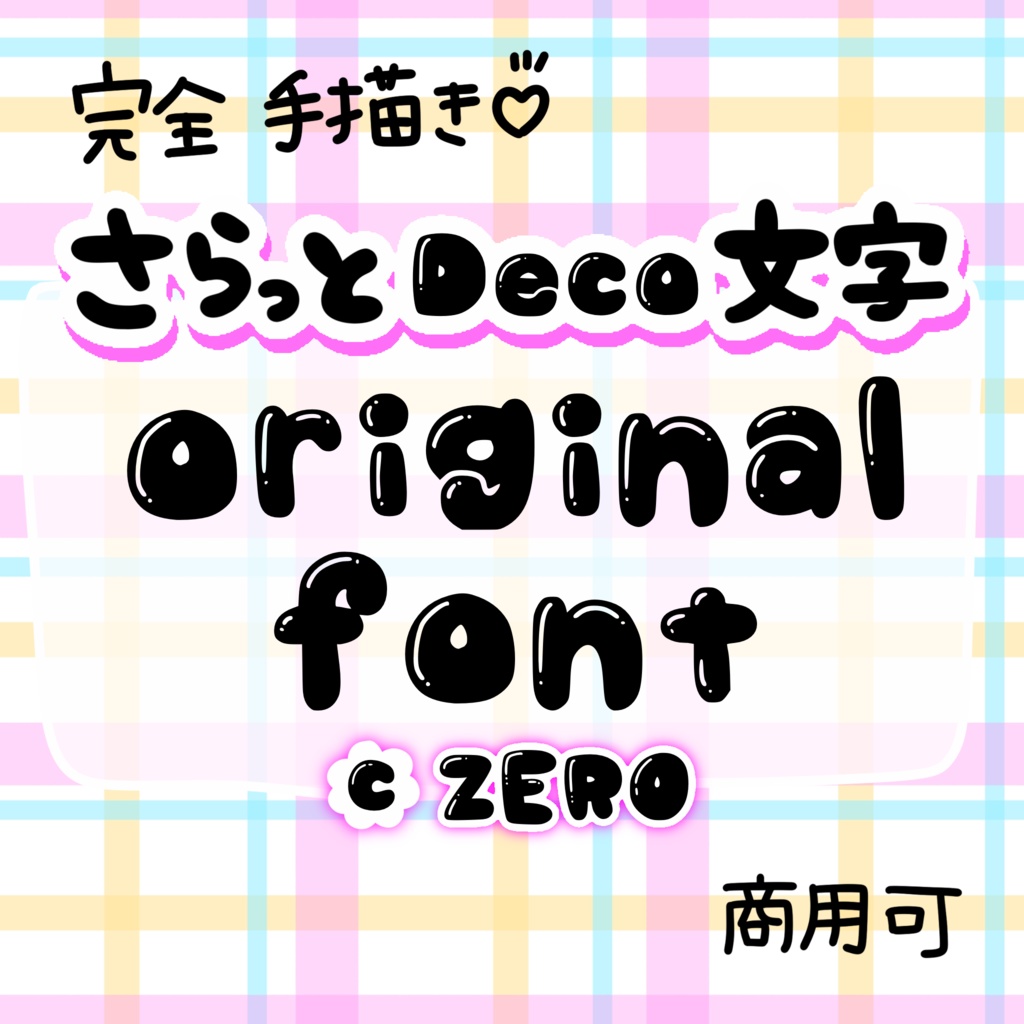
ZERO.さらっとDeco文字/fontDigital300 JPY카트에 담기기프트 보내기About Gift完全手描きフォントです★ ABCDEFGHIJKLMNOPQRSTUVWXYZ abcdefghijklmnopqrstuvwxyz !?’,:/- 二次販売不可 商用利用可能★ アルファベットご購入たくさんありましたら、 日本語フォントも挑戦してみたいので、応援していただけると嬉しいです♪ZERO.Visit FANBOX!Illustration (Other)VTuber 汎用モデル ギャルZERO.5,000 JPYIllustration (Other)VTuber 汎用モデル 女の子ZERO.3,000 JPYIllustration (Other)VTuber 汎用モデル ペンギンZERO.1,000 JPYFontsmocomoco / fontZERO.500 JPYFontsguuumi / fontZERO.500 JPYFontsデコ文字フォントZERO.300 JPYIllustration & CG collectionsVTuberモデル 小さな動物 ねずみZERO.3,000 JPYIllustration (Other)VTuberモデル 小さな動物 さるZERO.3,000 JPYIllustration (Other)VTuberモデル 小さな動物 りすZERO.3,000 JPYIllustration (Other)VTuberモデル 小さな動物 らいおんZERO.3,000 JPYIllustration (Other)VTuberモデル 小さな動物 きつねZERO.3,000 JPYIllustration (Other)VTuberモデル ミニキャラ動物 犬ZERO.3,000 JPYGraphicsLive2D VTuber モデル 男の子ZERO.3,000 JPY3D CharactersVTuberモデル【量販用】男の子ZERO.3,000 JPYIllustration (Other)Live2Dモデル★VTuber【量販モデル】ZERO.3,000 JPYIllustrations【Live2D】VTuberモデル/おばけ猫ZERO.777 JPY더보기